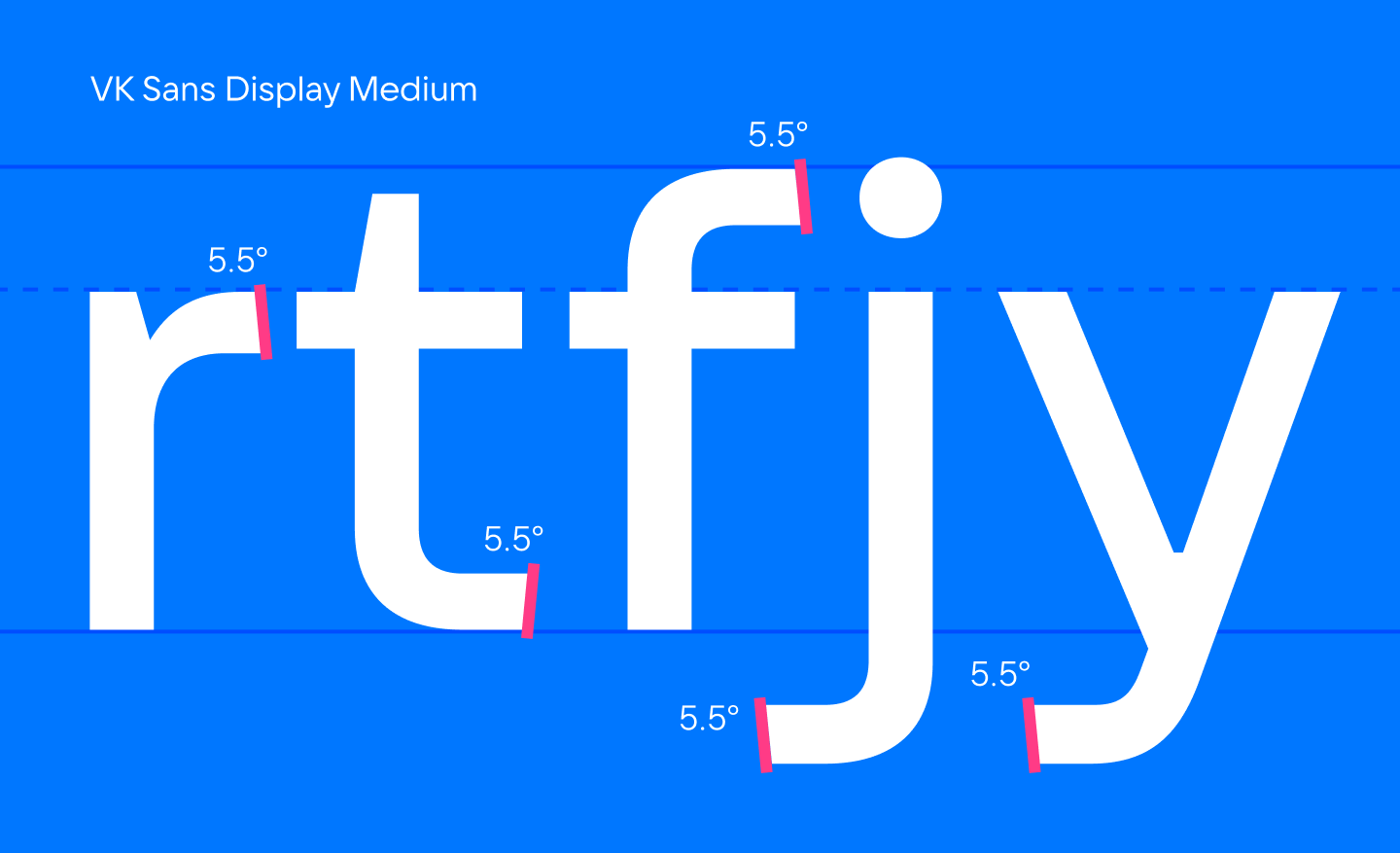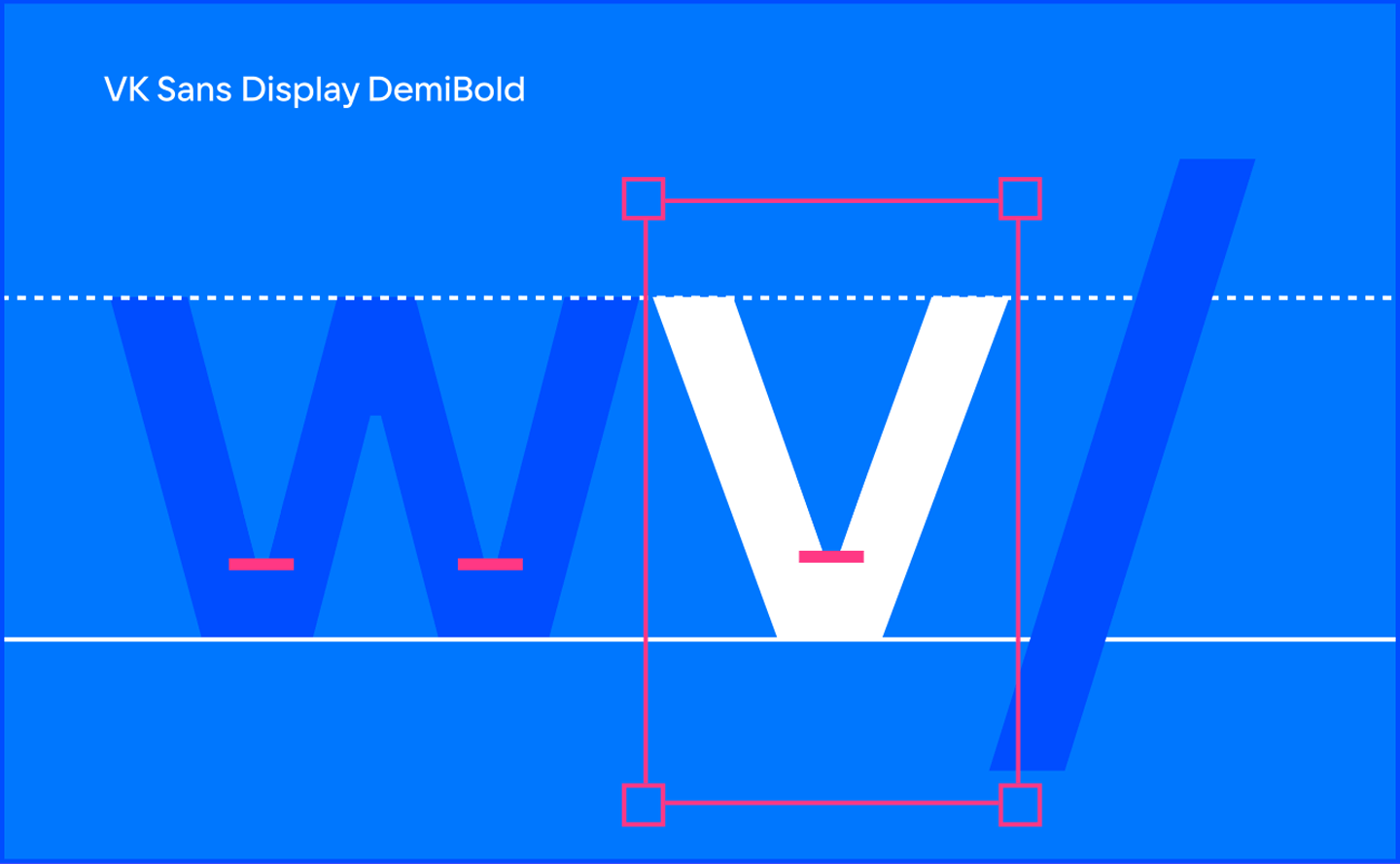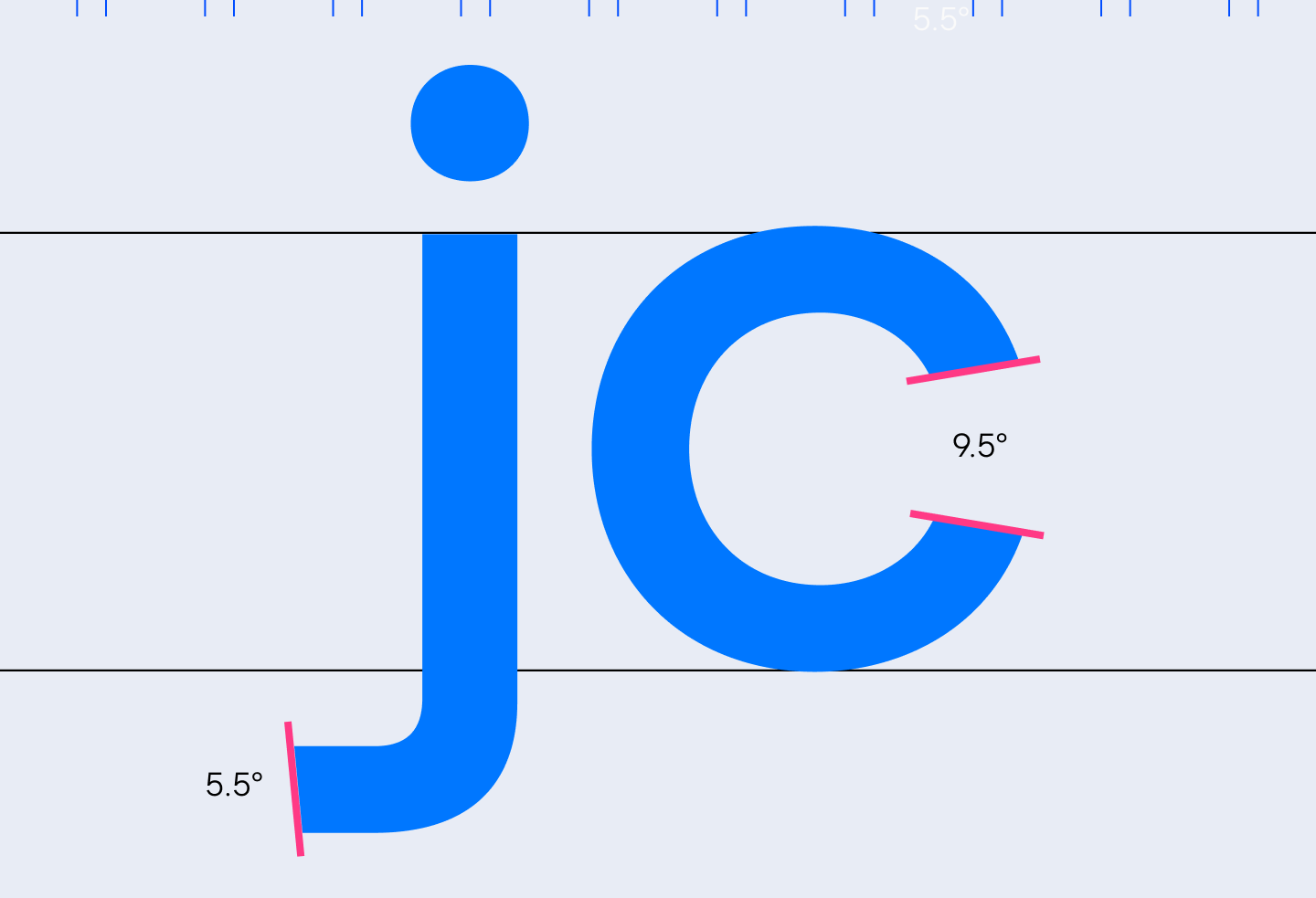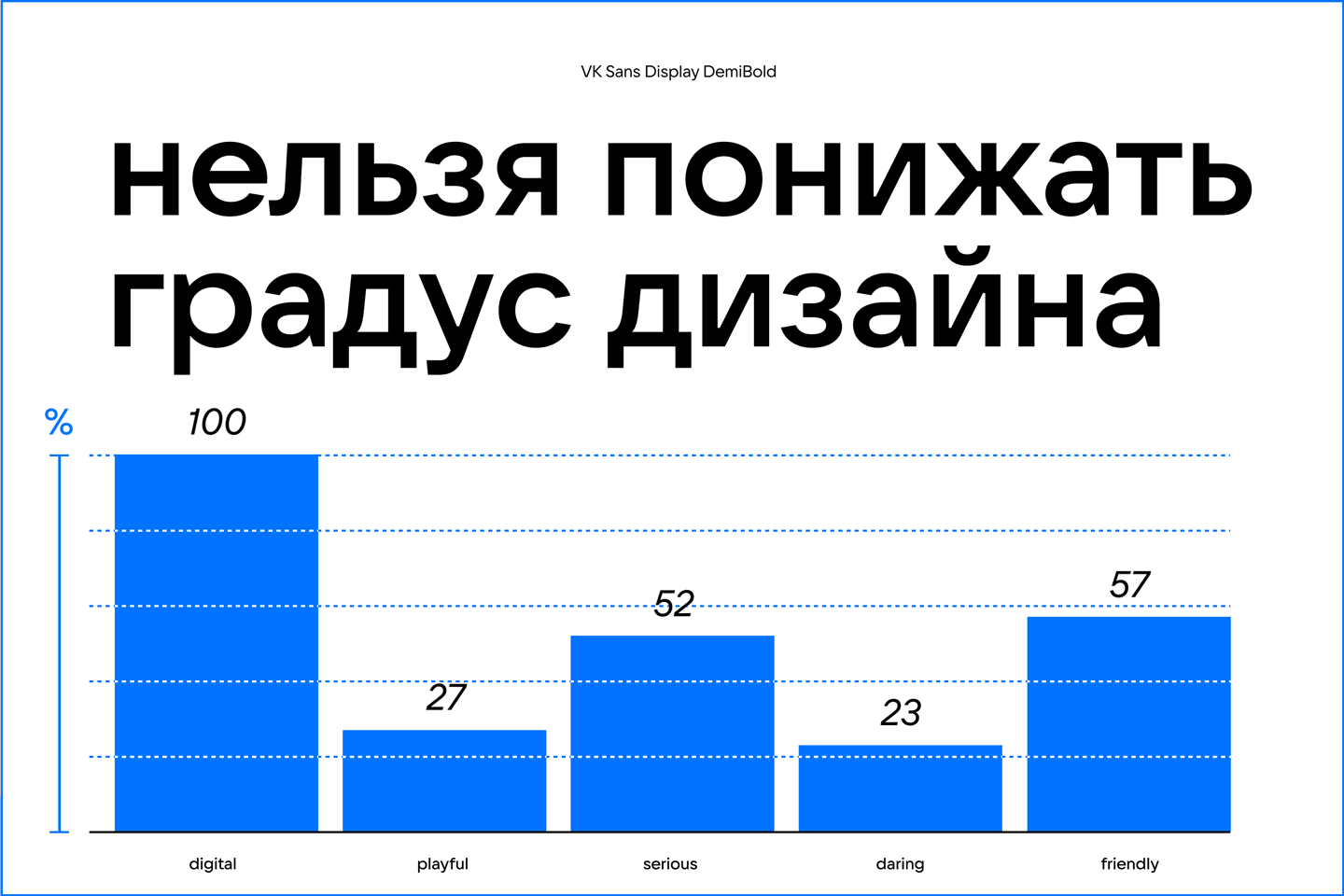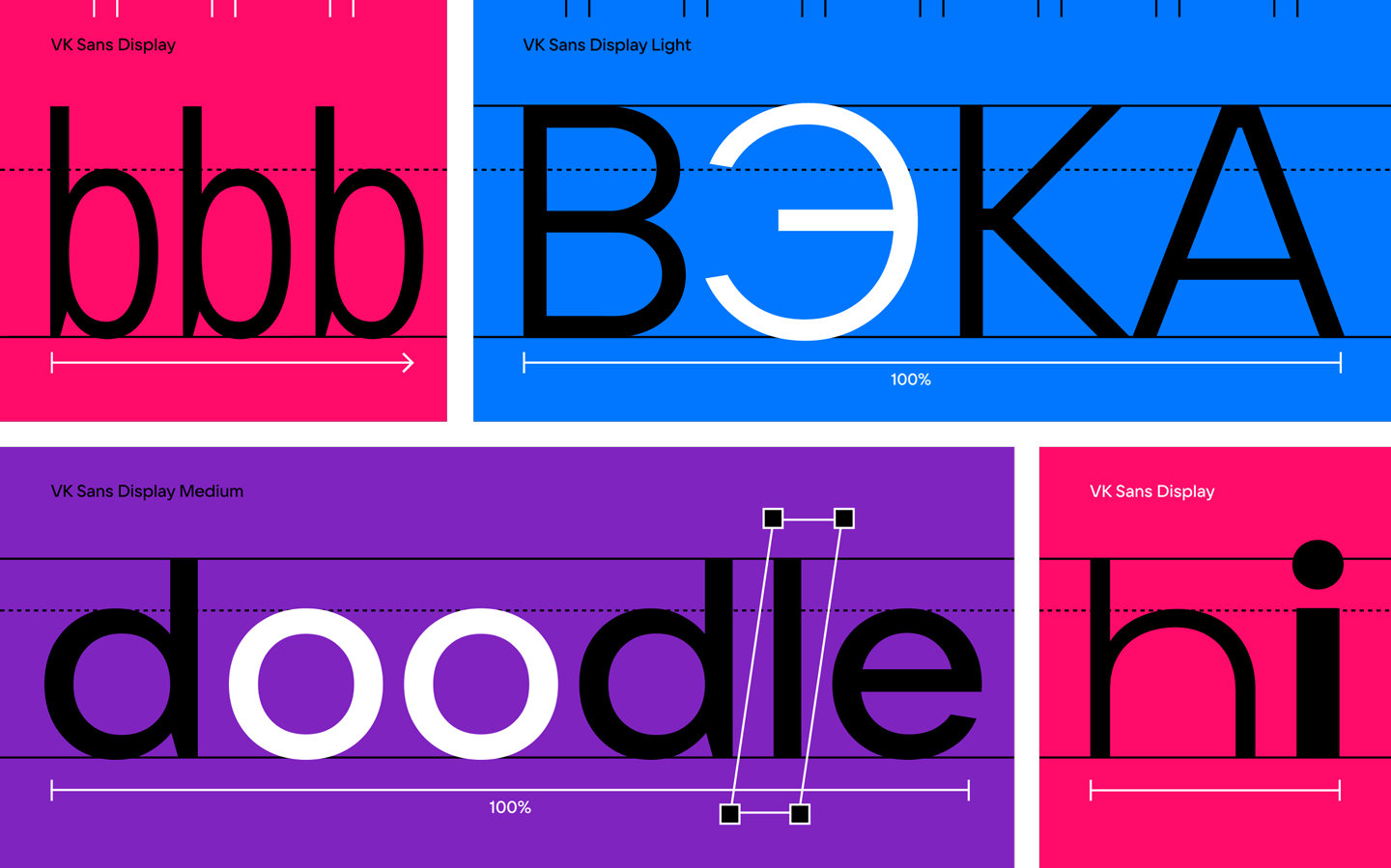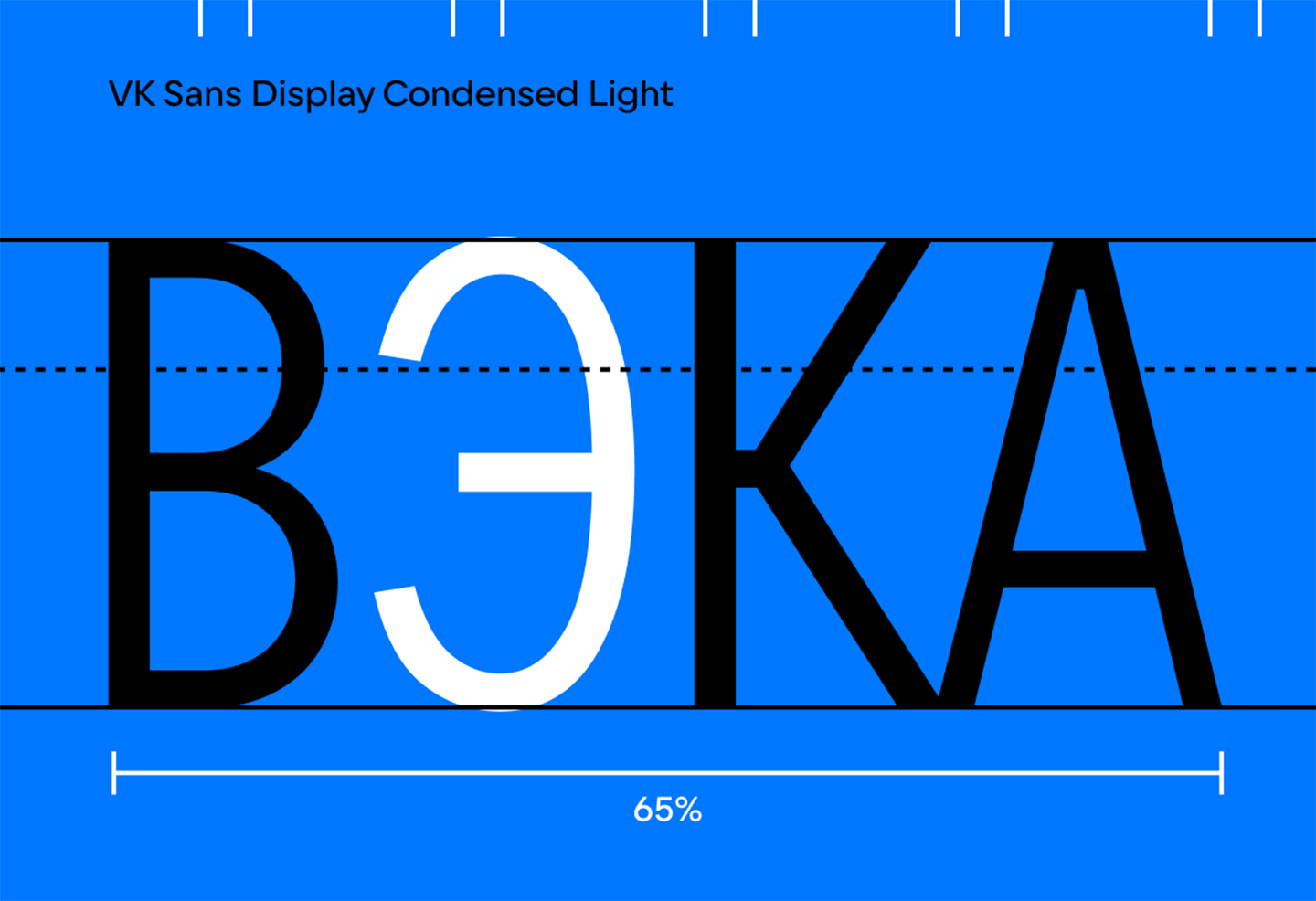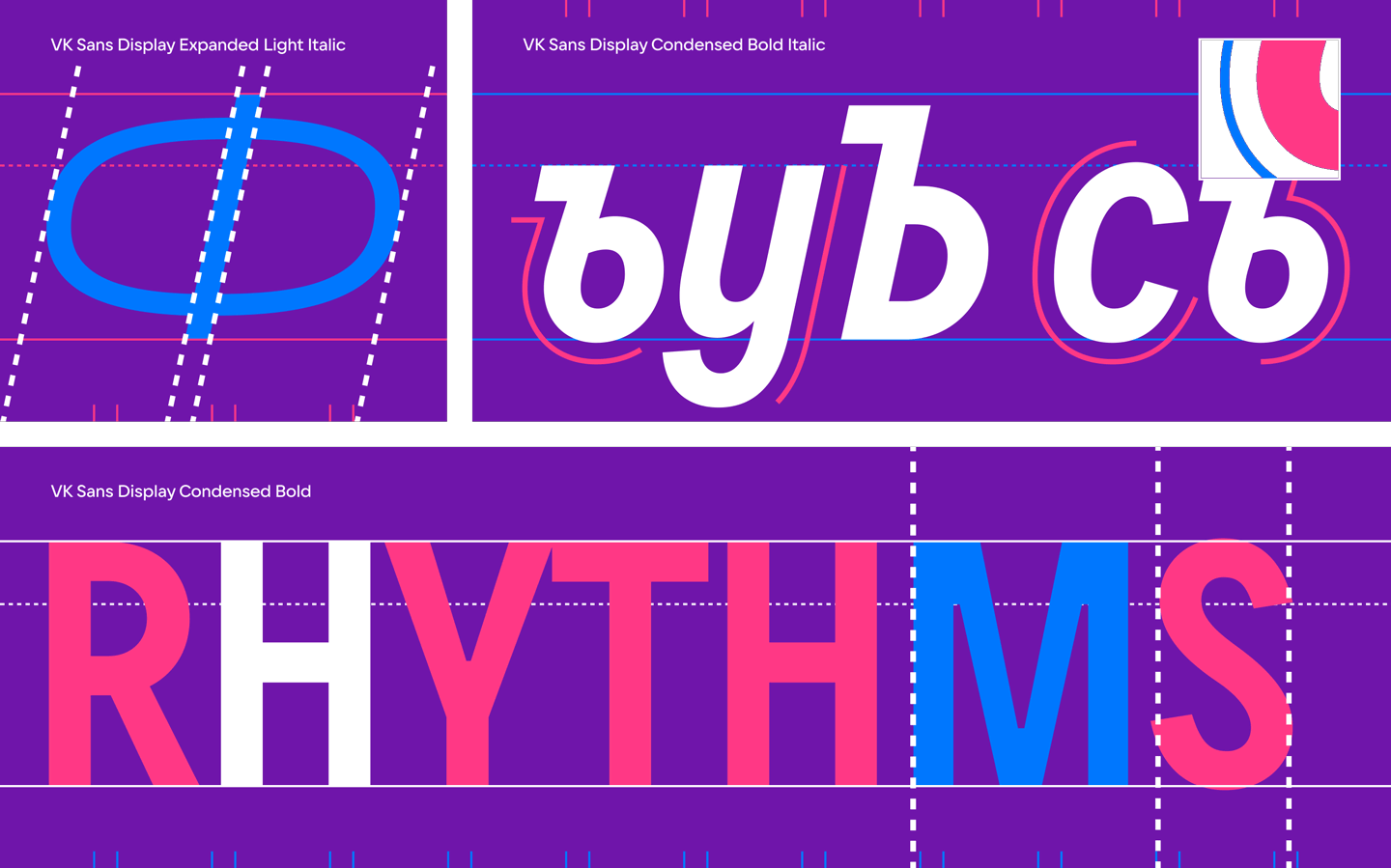
Как мы создавали фирменные шрифты для сервисов VK
Команда социальной сети ВКонтакте пришла к нам с глобальной задачей: сделать фирменную шрифтовую гарнитуру для соцсети, а точнее две (текстовую и дисплейную). Тогда мы еще не знали, что разработанное нами шрифтовое семейство станет основным не только для соцсети, но и для всей компании VK и ее сервисов: VK Музыки, VK Видео, VK Клипов, VK Знакомств и других.
ВКонтакте — самая популярная социальная сеть в России. Соцсетью пользуются больше ста миллионов человек во всём мире. Сейчас в рамках одного приложения или сайта пользователь может общаться с друзьями, смотреть клипы и видео, слушать музыку, совершать покупки и многое другое.
Часть первая. Шрифтовая пара
Первые встречи определили дальнейшую судьбу проекта. Ребята пригласили нас в свой офис в доме Зингера, чтобы поделиться планами и совместно выстроить тактику работы. Тогда мы и узнали, что в 2021 году Mail.ru Group приступает к масштабному ребрендингу, и будущие шрифты станут ключевым элементом айдентики разных продуктов VK.
Нас познакомили с проведенными исследованиями и тестами. Для пользователя социальная сеть ВКонтакте — это привычный и понятный продукт. Сохранить простоту и доступность было важно, но также хотелось добавить актуальности, узнаваемости и современности. Ещё одним фактором выступала универсальность шрифта, ведь ему предстояло нести разные эмоциональные сообщения в зависимости от сферы применения.
Чтобы обеспечить универсальность и сделать шрифт подходящим для разных задач, решили сделать два шрифтовых семейства: дисплейное и текстовое.
Давайте немного отвлечемся, чтобы прояснить, в чём ключевые отличия этих двух шрифтовых гарнитур.
• Дисплейный, или акцидентный шрифт — визитная карточка бренда. Ему позволено выглядеть более харизматично и обладать характерными графическими «фишками». В VK такой шрифт используется во всех коммуникациях и айдентике сервисов и спецпроектов.
• Текстовый, или интерфейсный шрифт — для комфорта пользователей. Именно он должен быть хамелеоном, подстраивающимся под различные задачи, обладать более спокойным и умеренным характером, вызывать чувство безопасности у пользователя. Текстовый шрифт является альтернативой системным шрифтам и используется на сайтах VK в больших блоках наборного текста.
В обсуждениях мы поняли, что на дисплейный шрифт возлагается ответственность за узнаваемость и современность восприятия, а вот текстовый должен отвечать параметрам простоты и доступности для пользователя. Более того, VK не хотела, чтобы эти шрифты были слишком похожими.
На практике текстовый шрифт часто становится лишь более спокойной версией дисплейного, но в нашем случае это должна быть пара из разных по характеру и в то же время идеально подходящих друг другу шрифтов.
Начать решили с дисплейного. У нас было три месяца до дедлайна, поэтому на первых двух встречах мы определили количество начертаний, кассовый состав шрифтов и основные размеры для использования.
Мы наполнили чашки кофе, и работа пошла.
Часть вторая. Дисплейное семейство
В первую очередь мы приступили к тестам на основе референсов, предоставленных командой VK. По итогу встреч мы знали, на что ориентироваться и где черпать вдохновение при работе над шрифтами.
Мы также определились с основными параметрами шрифта:
• размеры от 20 кегля;
• из начертаний Light, Regular, Medium, SemiBold, Bold;
• кассовый состав из 4 языков, цифр, спецсимволов, пунктуации и логотипа VK.
Стартовать решили с кириллицы и начертания SemiBold, которое VK планировала использовать чаще остальных.
Среди референсных шрифтов TypeType были выбраны TT HovesTT Commons и TT Interphases. Прежде чем приступить к работе, мы провели обширное исследование по сочетанию дисплейного и текстового шрифтов в разных вариациях, чтобы найти оптимальную комбинацию различий и сходств. Это было необходимо, чтобы впоследствии наши шрифты не стали слишком похожи, но идеально работали в паре и дополняли друг друга.
Например, это хорошо видно на фирменной шрифтовой паре Uber: Uber Move Display и Uber Move Text. Их дисплейный и текстовый шрифты отличались в принципиальных моментах, при этом гармонично сочетаясь.
Изучение кейсов помогло нам выстроить верную стратегию по нашим шрифтам и приступить к скетчам.
Так как мы подробно разобрали пожелания команды VK на первых двух встречах, работа продвигалась быстро.
Помимо вышеперечисленных параметров узнаваемости, современности и актуальности, стояла задача сделать дисплейный шрифт максимально интуитивным и простым в использовании, ведь гарнитурой будут пользоваться в том числе сторонние подрядчики и дизайнеры. Поэтому мы приняли решение убрать из шрифта все альтернативные элементы, такие как стилистические сеты, лигатуры и старостильные цифры.
Несмотря на яркий характер дисплейной гарнитуры, излишне вычурные или необычные акценты в графике знаков должны были отсутствовать, так как шрифт хотелось видеть универсальным.
Конечно, несмотря на приоритетность акцидентного шрифта, мы не могли подходить к задаче разрозненно, поэтому уже на первых скетчах комплексно прорабатывали основные особенности обоих шрифтов. Референсом для контуров текстового шрифта стал TT Interphases, вдохновив команду на наброски такого же универсального и современного шрифта. Однако уже на этом этапе новая шрифтовая гарнитура обрела уникальные черты.
Про графические отличия текстовой и акцидентной шрифтовых гарнитур VK расскажем чуть позже, а сейчас раскроем все технические нюансы дисплейной.
Перед погружением предлагаем вспомнить элементы типографики, о которых пойдёт речь.
• Стем — основной штрих буквы. Может быть вертикальным, как в букве Т, или наклонным, как в А.
• Влития — места соединения прямых штрихов с дугами, например, место стыка штрихов в n.
• Арка — дугообразная часть знака, например, выпуклая часть буквы о или дуга в букве n.
• Терминал — окончание штриха без засечки. Например, нижняя часть в букве t.
• Апертура — степень открытости некоторых знаков. В круглых буквах с разрывом, таких как с или е, это величина разрыва окружности. Чем меньше это расстояние, тем более закрытой будет апертура.
Уже на первом скетче мы разработали основную графику символов.
• Срезанные окончания стемов и контрастные влития в арках придавали шрифту аутентичность.
• Терминалы в арках приобрели нестандартный срез под небольшим углом, усиливая характерность шрифта.
• Срезы терминалов в fty и похожих знаках также заканчиваются под небольшим углом.
• Выраженные полочки в треугольных знаках при широком основании — фишка шрифта.
На этапе первого скетча мы уже прислали основную кириллицу и латиницу, а также сравнительные слайды с текстовым шрифтом.
Во второй скетч были внесены незначительные изменения, основная работа шла над деталями.
• Мы изменили горизонтальные срезы на более закрытые. Работали над гармонией сочетаний горизонтального и вертикального срезов.
• Букву в сделали чуть шире, шли обсуждения финального вида ф. Убрали полочки в треугольных знаках.
• Сделали экспериментальный скетч с более выразительной графикой некоторых символов.
После третьего скетча мы доработали знаковый состав, прорисовав его полностью. Работы над графикой оставалось немного, в основном мы детально прорабатывали какие-то моменты, например, внешний вид полочек разных символов.
Значительные изменения коснулись лишь стрелочек, итоговый внешний вид которых родился в результате графических поисков. В финале они стали компактными и аккуратными.
Мы доделали остальные начертания шрифтового семейства, доработали мелкие правки и отправили финальный файл шрифтовой гарнитуры, получившей название VK Sans Display.
Стильный и яркий, он сохранил умеренность и универсальность. Кстати, мы не смогли удержаться и сделали хинтинг, хотя это не обсуждалось. В шрифте всё должно быть прекрасно, не так ли?
Дисплейным шрифтом VK оформляют баннеры и постеры, используют его в видео и рекламе, дизайне мерча, логотипах сервисов и других коммуникациях.
Часть третья. Текстовое семейство
После завершения работы над дисплейной гарнитурой мы приступили к разработке текстового (или интерфейсного) шрифта. Перед началом работы организовали ещё одну встречу, чтобы обсудить промежуточные этапы и дополнительно пройтись по техническим особенностям.
Основные параметры для текстового шрифта у нас уже были:
• маленькие размеры: 20, 14, 12 и меньше;
• из начертаний Light, Regular, Medium, SemiBold, Bold;
• кассовый состав из 17 языков на кириллице и 33 на латинице, цифр, спецсимволов, пунктуации и логотипа VK.
До разработки фирменного шрифта VK в качестве системных шрифтов использовал три разных варианта в зависимости от платформы. Для IOS это был San Francisco, для Windows — Segoe UI, а для Android — Roboto. Это немного мешало цельному восприятию сервисов VK пользователем, и именно эти шрифты должен был заменить VK Sans Text.
Команда VK поделилась результатами своих тестов и подробно рассказала нам про технические нюансы, важные при разработке текстового шрифта. Главными факторами выступали компактность шрифтовой гарнитуры и читаемость в маленьком размере.
Мы приступили к внутренним исследованиям и первым скетчам.
Нам было важно сделать новый шрифт оригинальным, но при этом сохранить ощущение комфорта у пользователя. Ещё одной задачей стала совместимость с системными шрифтами на случай, если пользователю придётся напечатать символы, отсутствующие в фирменном шрифте. Мы решили эту задачу, сделав параметры шрифта похожими на системные по высоте, толщине и разрядке.
В этом шрифте ведущим начертанием был Regular, с которого мы и начали работу. Первые наработки мы делали в кириллице и латинице, в презентационных материалах предоставляя совместные исследования текстового и дисплейного шрифтовых семейств.
Работа шла более плавно, мы попеременно вносили правки в шрифт, которые возникали и со стороны VK, и с нашей. Постепенно шрифт приобретал желаемые черты.
Различий с дисплейным шрифтом, необходимых для уникального облика гарнитуры, было достаточно.
• Строчные знаки в текстовом шрифте стали выше, чтобы улучшилась читаемость.
• Знаки стали стремиться к равноширинности, контраст в ширинах ушёл. Так мы достигли компактности.
• Круглые формы обрели сквадраченность, что также улучшает читаемость шрифта в мелком размере.
• Присоединение арок и полуовалов стало жесткое, что добавило динамики, улучшающей читаемость и восприятие.
• Межбуквенные расстояния стали больше. Классическое отличие текстового шрифта относительно дисплейного.
• Апертуры стали более открытыми, что тоже является одним из классических изменений при разработке текстового и дисплейного шрифтов.
Когда была готова большая часть наработок, мы начали расширять кассовый состав и вносить изменения в графику символов относительно первого скетча. Например, убрали диагональные срезы в буквах, экспериментировали со спейсингом, изменяли внешний вид цифр и добавляли в шрифт необходимые фичи. После каждой итерации VK забирала наработки на тестирование, после возвращалась и вносила изменения. Пошла точечная работа по совершенствованию шрифта.
Интересная история случилась с трекингом, то есть изменением расстояния между буквами в зависимости от кегля. VK загорелась идеей сделать трекинг, автоматически подстраивающийся под размер шрифта, чтобы улучшить читаемость — как Apple сделали для San Francisco. Проблема заключалась в том, что в случае яблочной компании это решение — системное, и по аналогу сделать было невозможно.
В процессе обсуждений и исследований появилось два способа решения задачи:
• разработать несколько шрифтов с разным трекингом, которые VK самостоятельно загрузит в систему;
• прописывать трекинг в вебе.
Изначально ребята склонялись ко второму варианту, и мы провели обширное исследование по гармоничному сочетанию трекинга и размера шрифта, предоставив команде VK таблицу с результатами. Позже мы остановились на первом варианте. Чтобы система работала быстрее, выбрали 4 шрифта для разных размеров.
На этом этапе мы уже согласовали все начертания шрифта и предоставили полный кассовый состав. VK проводила обширные исследования, возвращаясь к нам с результатами.
Например, одно из исследований было пользовательским, и изучало изменения в восприятии прошлых системных шрифтов и разработанного нами. К счастью, интерфейс приложения с новым шрифтом остался комфортным для пользователей, а, значит, VK Sans Text подходит для использования в приложении.
Часть четвёртая. Техническая работа
Техническая работа над шрифтом часто остаётся за ширмой для зрителя, ведь её нельзя увидеть так же наглядно, как графическую. Однако именно эта составляющая превращает набор нарисованных символов в рабочую шрифтовую гарнитуру, удобную и функциональную.
Над шрифтами VK техническая работа велась особенно тщательно, ведь задача стояла глобальная, а на наши шрифтовые гарнитуры возлагалась большая ответственность за комфорт пользователей социальной сети и других сервисов бренда.
Мы не будем раскрывать все детали, но подробно остановимся на хинтинге, который делали при разработке шрифтовых семейств VK Sans Text и VK Sans Display.
Хинтинг — визуальная разметка, то есть набор правил и подсказок, благодаря которым контуры знаков шрифта выглядят более чётко и читаемо в маленьком размере и при плохом разрешении экрана. Это сложный технологический процесс, часть которого делается вручную.
Мы с самого начала понимали и учитывали тот фактор, что наши шрифты будут работать на всех браузерах и платформах: Mac OS, iOS, Windows, Android и других. Каждая обладает своими правилами и характеристиками, влияющими на шрифт. Например, Mac OS использует свою систему растеризации Quartz, игнорируя инструкции хинтинга из шрифтового файла. Однако для Windows, Android и других платформ хинтинг важен, и чем подробнее прописаны правила вывода глифов, тем лучше будет читаемость шрифта.
Несмотря на то, что мы улучшали параметры читаемости шрифта уже на этапе прорисовки букв, хинтингу было отведено особое место в работе. Он стал завершающим этапом целого комплекса мер, дополнив правильную графику знаков, оптимальную разрядку и многое другое.
Мы делали хинтинг с особым вниманием к деталям, чтобы в результате:
• повысить читаемость;
• создать правильный спейсинг, то есть исключить слипание букв при любом размере;
• обеспечить шрифту контраст, заложенный дизайнером;
• создать ровную строку во всех размерах.
Для шрифтов VK мы использовали хинтовщик Visual TrueType, а также собственный софт, позволяющий поглифно переносить хинты между шрифтами. Несмотря на технологичность этих процессов, часть контуров мы правили вручную, чтобы достичь максимального качества отображения шрифтов.
Текстовая шрифтовая гарнитура заранее планировалась для использования в меньших размерах, чем дисплейная, поэтому хинтингу шрифтового семейства VK Sans Text мы уделили особое внимание. Благодаря тестированию и корректировкам мы смогли достичь своих целей и сделать VK Sans Text хорошо читаемым на разных устройствах и экранах.
Несмотря на глобальность задач, мы справились с разработкой дисплейного и текстового шрифтов довольно быстро. Наверное, такой динамичной и слаженной работы было бы труднее достичь без вовлечённости команды VK, чёткого описания целей и пожеланий, а также оперативной коммуникации.
В результате мы получили шрифтовую пару, состоящую из харизматичного дисплейного шрифта и компактного текстового. Несмотря на различия в характере гарнитур, они универсальны в использовании. С помощью ряда нюансов мы сделали эту пару идеально подходящей друг другу.
Часть пятая. Расширение гарнитуры
После того, как дизайнеры из команды VK плотно поработали с новыми шрифтами, они поняли, что базовых начертаний им уже не хватает. Ведь бренд продолжает активно развиваться, и вместе с этим появляются новые потребности. Поэтому ребята обратились к нам с новой задачей — создать новые начертания для дисплейного семейства, чтобы с их помощью разнообразить коммуникацию и повысить градус дизайна, а также, когда нужно, придать шрифту более акцидентное, актуальное звучание.
В итоге мы решили разработать два новых подсемейства для VK Sans Display: узкое Condensed и широкое Expanded, а также нарисовать италики для них и уже существующих базовых начертаний.
Перед нами стояла интересная задача — действовать в рамках существующего дисплейного шрифта, в котором уже задан уровень и стиль акциденции. В оригинальном VK Sans Display он сдержанный, но при этом цепляющий: увидев шрифт во второй раз, вы точно его узнаете. Нам нужно было немного раскрепостить, добавить в детали динамики, какую-то изюминку. И при этом оставить новые подсемейства узнаваемыми, не изменив характер VK Sans Display.
В самом начале работы над расширением мы с командой VK договорились о регулярных созвонах, во время которых показывали процесс разработки и получали быструю обратную связь. На одном из первых таких онлайн-встреч мы показали несколько вариантов сужения и расширения оригинального шрифта — максимальное сужение до 55% от VK Sans Display и расширение до 145%. Опытным путем мы пришли к выводу, что большая деформация привела бы к чрезмерной акциденции, и область применения шрифта бы заметно сузилась.
Также мы продемонстрировали промежуточные варианты деформации ширин. В итоге остановились на промежуточном варианте для Condensed и на самом широком — 145% от нормальной ширины — для Expanded. Кроме того, мы показали варианты узких и широких символов с различной степенью акциденции, чтобы в диалоге с командой VK лучше понять их нужды.
Затем мы показали уже полноценные скетчи сразу для всего семейства. Condensed и Expanded в двух весах — самом тонком и самом жирном, а также два варианта графики для начертания Italic — просто наклонные шрифты и тру-италик, в котором формы графем строчных знаков меняются на более округлые, рукописные. Команда VK выбрала вариант с наклонными шрифтами, но мы не удержались и дополнительно сделали тру-италик сет.
Дальше работа пошла по стандартной схеме: отрисовка алфавитов, цифр, пунктуации, служебных символов. После согласования прямых начертаний мы отрисовали италики к каждому из них, а также к оригинальному VK Sans Display. Затем все шрифты отправились на техническую доработку: мастеринг, кернинг и хинтинг.
Забавно, что в первоначальном ТЗ подсемейства Condensed и Expanded должны были состоять из трех весов. Но, как известно, аппетит приходит во время еды, и в результате в этих подсемействах по пять начертаний — то есть столько же, сколько в оригинальном VK Sans Display. В процессе разработки мы давали ребятам из VK тестировать промежуточные версии шрифта в разных весах, и они остановились на таком варианте. Подобный подход к подбору весов и ширин возможен благодаря технологии вариативного шрифта.
Подводим итоги (но не прощаемся)
В результате нам удалось сохранить узнаваемые детали оригинального VK Sans Display: например, формы «Лл», «Дд» и срезы в терминалах. Кроме того, появились и новые решения, повышающие уровень акцидентности. Так, окружности стали более сквадраченными, изменились влития в некоторых знаках, таких как «р» и «d». В наклонную версию шрифтов мы добавили тру-италик сет, при включении которого графемы строчных знаков меняются на более округлые, рукописные. Это позволяет менять настроение дизайна и расставлять акценты в коммуникации.
Итак, в итоге у нас получилась функциональная шрифтовая система, включающая дисплейный и текстовый шрифты.
VK Sans Display cостоит из трех подсемейств: VK Sans Display, VK Sans Display Expanded, VK Sans Display Condensed. В каждом из них — начертания Light, Regular, Medium, SemiBold, Bold и италики к ним. Дисплейный шрифт поддерживает 63 языка.
VK Sans Text состоит из начертанйи Light, Regular, Medium, SemiBold, Bold и поддерживает 199 языков.
При разработке мы постарались предусмотреть и внедрить в шрифт максимальное количество возможностей. Широкие начертания очень органично вписываются в дизайн макетов и гармонично смотрятся рядом с классическим шрифтом VK.
В качестве приятного бонуса мы внедрили новый логотип VK во все шрифты (в оригинальном VK Sans Display была старая версия логотипа со скруглениями). Кроме того, для оригинального VK Sans Display мы обновили кернинг, так как за последние два года наши методы в этом направлении продвинулись вперед.
А команда VK даже создала интерактивный сайт, посвященный VK Sans: vksans.ru. На его основе и были сделаны иллюстрации к этой статье.
Так что мы не ставим точку в этой истории. VK активно растет дальше, и мы готовы продолжать сотрудничество с их замечательной командой, вместе развиваться и работать над новыми захватывающими проектами.
Над проектом работали:
Команда TypeType
Марина Ходак — Развитие шрифтовой системы, автор дополнительных подсемейств
Юлия Гонина — Автор и дизайнер основного шрифта
Анастасия Погорелова — Старший шрифтовой дизайнер
Тома Стрельцова — Старший шрифтовой дизайнер, италики
Антонина Самохина — Шрифтовой дизайнер, италики
Иван Гладких — Кернинг
Виктор Рубенко — Хинтинг
Юрий Наконечный — Мастеринг, тестирование шрифтов